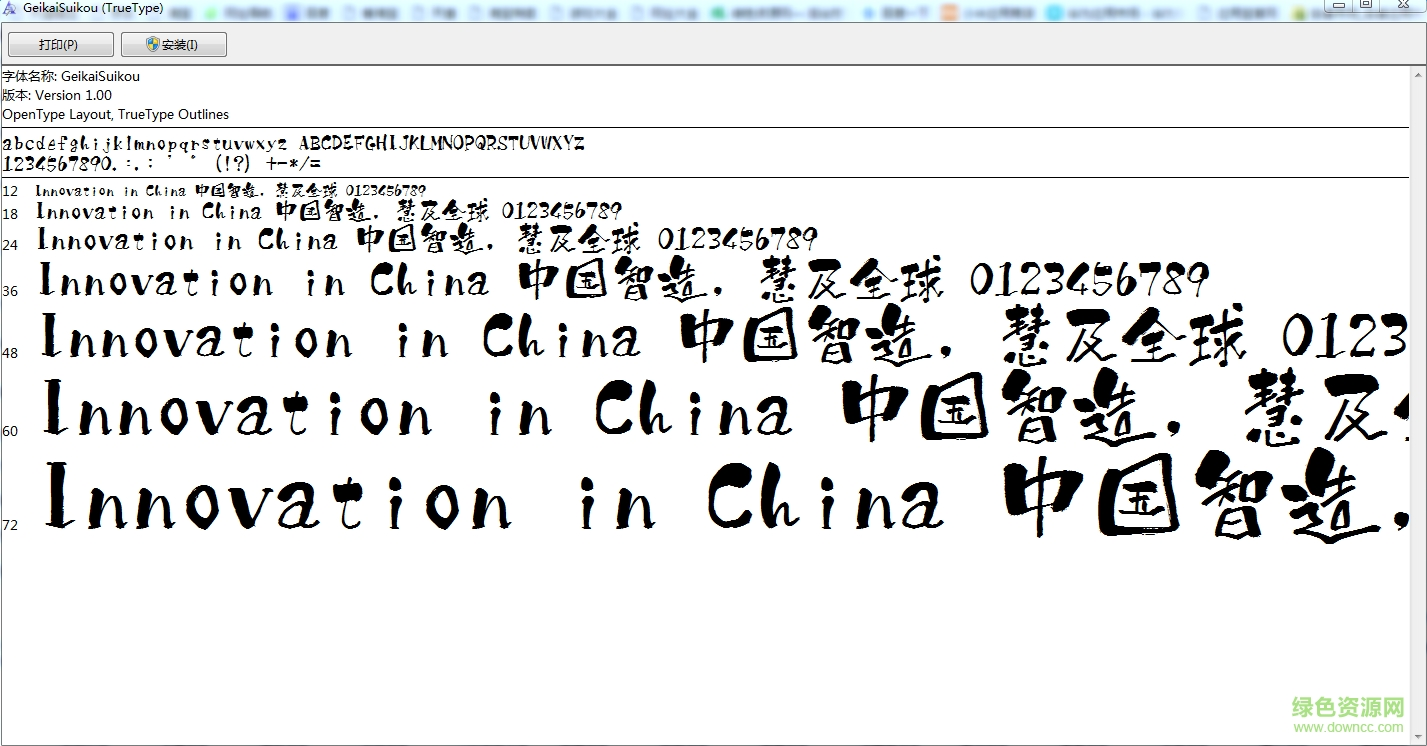
軟件介紹 軟件標簽: 白舟鯨海酔侯書體 白舟字體 白舟鯨海酔侯書體字體是一款獨特的白舟字體,線條粗壯,筆鋒瀟灑,字體整體設(shè)計感非常強,有需要的小伙伴歡迎在綠色資源網(wǎng)下載!字體安裝方法方法一:控制面板/字體/文件/安裝新字體;方法二:直接將字體復(fù)制到C:\WINDOWS\Fonts。方法三:針對win7系統(tǒng),用戶只需選中字體右鍵安裝即可。注意事項本站所有字體資源僅供個人學(xué)習與參考,如需商業(yè)使用請到相關(guān)官網(wǎng)授權(quán)。 軟件截圖 上一張下一張(1 / 1) 安裝詳細截圖 猜你喜歡 古風字體 藝術(shù)字體 古風字體 古風字體,顧名思義,就是有古代風韻的字體。這類字體一般給人的感覺,都是比較飄逸的,非常好看,很有意境,如:南構(gòu)唐寶楷字體、文悅古典明朝字體、葉根友古刻體字體等,喜歡的朋友,趕快下載體驗吧! 查看更多>> 南構(gòu)唐寶楷字體簡體 5.85M/中文/2.1/ttf下載 造字工房文研常規(guī)體 1.04M/中文/10.0/下載 漢儀曉波折紙體 823KB/中文/10.0/下載 白舟鯨海酔侯書體 3.16M/中文/10.0/ttf版下載 白舟隼風毛筆書法字體 4.19M/中文/10.0/下載 白舟草書教漢字體 464KB/中文/10.0/下載 藝術(shù)字體 藝術(shù)字體下載大全免費打包專題是小編專為廣大字體控朋友們整理的經(jīng)典藝術(shù)字體大合集,包含了各式各樣的書法藝術(shù)字體和個性藝術(shù)字體,整體效果十分出眾! 查看更多>> 華為伯樂油畫體 2.05M/中文/10.0/ttf免費版下載 鄭板橋書法字體 795KB/中文/0.0/下載 孫過庭草體測試版 1.37M/中文/10.0/下載 淡齋草書字體 2.92M/中文/8.5/下載 白舟太篆書體字體 2.36M/中文/3.3/下載 白舟靜月書體字體 1.12M/中文/10.0/下載 其他版本下載 標題 大小 更新日期 下載 下載地址 電腦版 白舟鯨海酔侯書體 ttf版 點擊報錯 軟件無法下載或下載后無法使用,請點擊報錯,謝謝! 關(guān)閉報錯反饋 請描述您所遇到的錯誤,我們將盡快予以修正,謝謝! *必填項,請輸入內(nèi)容 本類最新 dreamweaver字體庫 首爾南山體字體 v1.06 官方版 潮字社風云簡ttf 潮字社凌渡鯤鵬簡體字體 潮字社曾玉波手書簡字體 微博慧心字體 用戶評論 熱門評論 最新評論 發(fā)表評論 查看所有評論(0) 昵稱: 請不要評論無意義或臟話,我們所有評論會有人工審核. 字數(shù): 0/500 (您的評論需要經(jīng)過審核才能顯示)